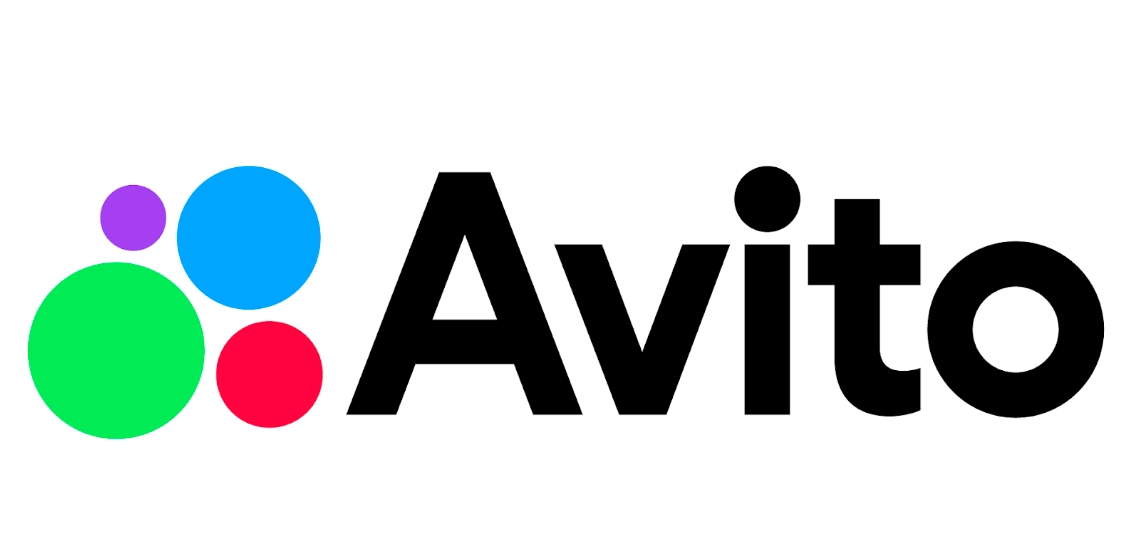
«Авито» исполнилось 15 лет, и в честь этого события компания обновила дизайн платформы. Изменили логотип, фирменные цвета и надписи. Рассказываем, как теперь выглядит брендинг «Авито».
Новый логотип «Авито»
Ключевым изменением стал новый логотип доски объявлений. На нем все так же остались четыре круга разного размера, однако они стали ярче и располагаются теперь по-другому: большие круги отразили по вертикали, а меньшие — по горизонтали (кстати, у нас вы можете заказать логотип — прим. отдела продаж TexTerra).
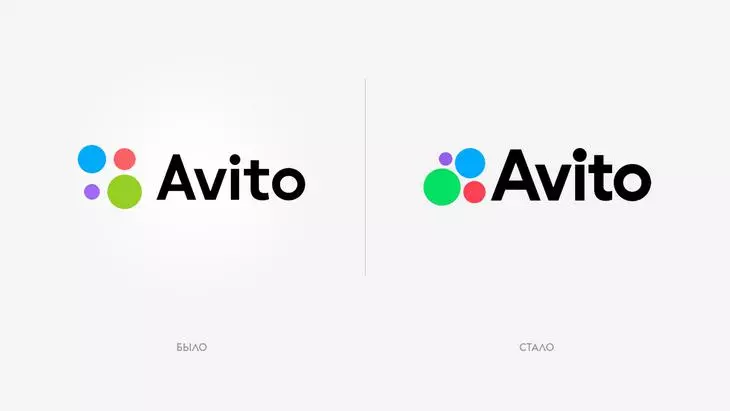
Зеленый круг стал соотноситься с буквой «o» на конце названия компании — в логотипе их размеры одинаковы. Таким же образом фиолетовый круг в креативном агентстве соотнесли с точкой над буквой «i».
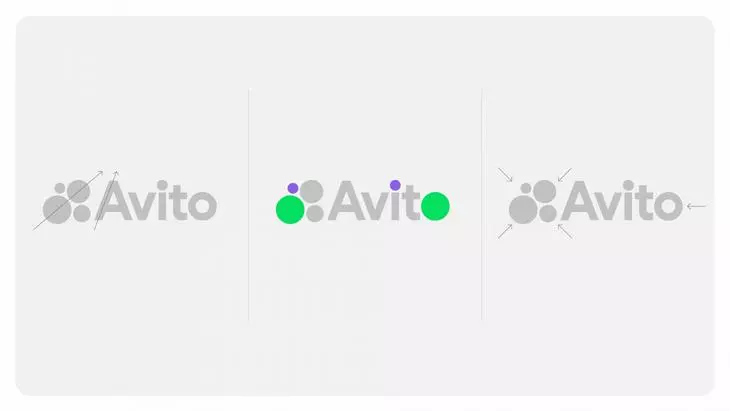
Элементы лого стали ближе друг к другу, а палитра цветов бренда — более яркой. Кроме того, круги теперь не просто элемент дизайна — они символизируют разделы «Авито»: Товары, Авто, Недвижимость и Работу с Услугами.
«Авито» стал взрослее и больше. Бренду понадобился соразмерный образ. Мы сделали прямую иллюстрацию его психоэмоциональных характеристик: наполненное притягивающимися шарами, тесное, но комфортное яркое пространство. Повсюду всплеск цвета. Это своего рода живопись цветового поля, символизирующая что-то намного менее конкретное, чем булавку. Это место, где продавцы и покупатели притягиваются, смешиваются и растворяются.
Дарья Зудина, арт-директор бренд-бюро «Щука»
Новые фирменные цвета и шрифт
Вместе с логотипом агентство «Щука» сделало для «Авито» и новый брендбук. В него, помимо цветовой палитры, вошла новая фирменная графика, в которой круги с логотипа принимают различные формы — растягиваются в полосы или заключаются в квадрат.
Изменилась и типографика — теперь для логотипа и вообще всего визуального оформления «Авито» используется шрифт Aeroport. Он жирнее того, что был раньше, и в целом выглядит немного плавнее предшественника.
В целом, визуальный стиль «Авито» стал посовременнее — в нем сместились акценты, цвета стали ярче, а элементы минималистичнее. При этом узнаваемость бренда и его фирменного стиля не изменится — ассоциирующиеся с «Авито» цвета и форму не исчезли, а немного изменились.
Очень забавно. Компоновка фирменного знака изменили больше для композиционной корректировки, а вот систематическое изменение меня больше всего порадовало. Равнозначные отступы элементов друг от друга отлично выглядят. Таким образом фирменный знак стал более устойчивым. Типографика логотипа также изменила стиль и соответствует фирменному знаку. Также она выполнена с изменениями стиля межбуквенного расстояния. Это сделало фирменный блок более собранным.